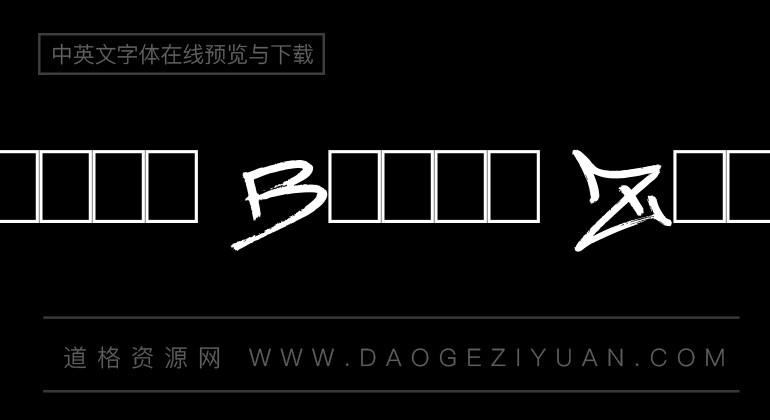
Urban Brush Zone 字体是一款卡通和涂鸦风格的手写体字体。它具有易读性强,更有助于增强文字的视觉效果,带有活泼和欢乐的气氛。它可以用于印刷品,书籍,海报,宣传单,网页,游戏等等,可以帮助人们更好地理解文字,并且可以让文字和图片更好地结合在一起。内容介绍
Urban Brush Zone是一款非常不错的手写艺术字体,具有很好的视觉感,适合于文化类的宣传设计、商业类品牌的广告和产品包装设计以及个性化文字排版等较多场景。